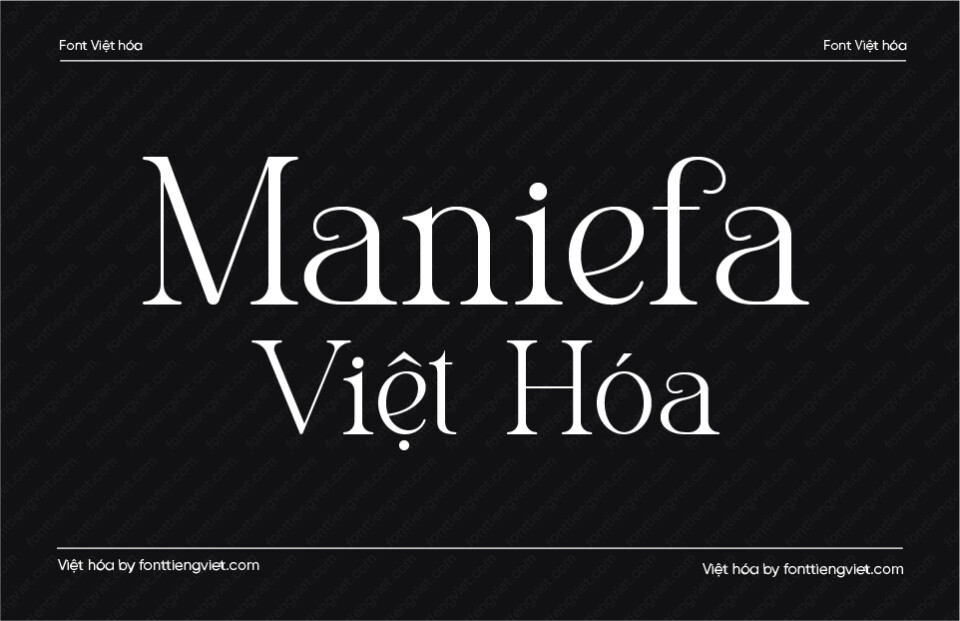
Font Việt hóa 1FTV VIP Maniefa – Bộ Font Sang Trọng Cho Thiết Kế Chuyên NghiệpTrong thế giới đồ họa hiện đại, việc lựa chọn một bộ Font Miễn Phí chất lượng luôn là ưu tiên hàng đầu của các nhà thiết kế. Font Việt hóa 1FTV VIP Maniefa nổi lên như một hiện tượng nhờ sự kết hợp hoàn hảo giữa nét cổ điển và hơi thở đương đại. Đây là bộ font chữ được tinh chỉnh kỹ lưỡng, giúp người dùng tại Việt Nam dễ dàng truyền tải thông điệp mà không lo lỗi hiển thị tiếng Việt. Với những đường nét thanh mảnh nhưng chắc chắn, bộ font này thực sự là giải pháp tối ưu cho những ai đang tìm kiếm sự khác biệt và đẳng cấp trong từng con chữ.Khám phá vẻ đẹp độc đáo của Font Việt hóa 1FTV VIP Maniefa sở hữu cấu trúc hình học cân đối, tạo cảm giác dễ nhìn và chuyên nghiệp. Điểm nhấn của bộ font này nằm ở các nét serif tinh tế, giúp tăng cường khả năng đọc trên cả nền tảng in ấn lẫn kỹ thuật số. Khi sử dụng bộ chữ này, các thiết kế của bạn sẽ tự động toát lên vẻ sang trọng, lịch lãm, phù hợp cho nhiều mục đích khác nhau từ làm thương hiệu đến trang trí nội dung học tập.Ứng dụng đa dạng trong thiết kế đồ họaVới sự linh hoạt cao, Font Việt hóa 1FTV VIP Maniefa thường được ưu tiên sử dụng trong các mẫu thiết kế thiệp mời, bìa sách hoặc tiêu đề tạp chí. Trong môi trường giáo dục, giáo viên và học sinh có thể dùng font chữ này để làm slide thuyết trình thêm phần cuốn hút và chuyên nghiệp hơn. Những đường nét mềm mại nhưng dứt khoát của Maniefa giúp làm nổi bật các ý chính, giúp người xem dễ dàng ghi nhớ thông tin một cách tự nhiên nhất.Sự tối ưu cho tiếng Việt chuẩn xácMột trong những lý do khiến Font Việt hóa 1FTV VIP Maniefa được yêu thích chính là việc tích hợp đầy đủ các dấu thanh tiếng Việt. Các ký tự như “ă”, “â”, “ơ” hay các dấu hỏi, ngã được thiết kế đồng bộ với thân chữ, tránh tình trạng bị lệch dấu hay thay đổi định dạng đột ngột. Điều này cực kỳ quan trọng đối với các bạn học sinh khi làm bài tập lớn hoặc các nhà thiết kế cần sự chỉn chu tuyệt đối trong văn bản tiếng Việt.Tại sao nên lựa chọn Font Việt hóa 1FTV VIP Maniefa?Việc sở hữu Font Việt hóa 1FTV VIP Maniefa không chỉ giúp bạn tiết kiệm thời gian chỉnh sửa mà còn nâng tầm giá trị thẩm mỹ cho tác phẩm. Bộ font này hỗ trợ nhiều định dạng khác nhau, tương thích tốt với các phần mềm phổ biến như Adobe Photoshop, Illustrator hay Microsoft Word. Sự tỉ màng trong khâu việt hóa giúp font chữ này giữ nguyên được linh hồn của bản gốc nhưng vẫn rất gần gũi với người dùng Việt Nam.Cách kết hợp font chữ hiệu quảĐể phát huy tối đa sức mạnh của Font Việt hóa 1FTV VIP Maniefa, bạn nên kết hợp nó với các font không chân (sans-serif) đơn giản cho phần nội dung dài. Sự tương phản giữa nét sang trọng của Maniefa ở tiêu đề và sự gọn gàng của font nội dung sẽ tạo nên một bố cục hài hòa, dễ chịu cho mắt người đọc. Đây là quy tắc vàng giúp bản thiết kế của bạn trở nên tinh tế và đẳng cấp hơn hẳn các mẫu thông thường.Kết luận về bộ Font Việt hóa 1FTV VIP ManiefaTóm lại, Font Việt hóa 1FTV VIP Maniefa là một công cụ không thể thiếu trong kho tài nguyên của bất kỳ ai yêu thích cái đẹp và sự chuẩn xác. Dù bạn là một học sinh đang làm báo cáo hay một designer chuyên nghiệp đang xây dựng bộ nhận diện thương hiệu, bộ font này đều đáp ứng xuất sắc mọi yêu cầu khắt khe nhất. Đừng bỏ lỡ cơ hội sở hữu Font Miễn Phí, Font Việt Hóa, Font Việt hóa 1FTV VIP Maniefa để biến những ý tưởng sáng tạo của mình thành hiện thực một cách ấn tượng và đầy cảm hứng ngay hôm nay.
Font Việt hóa 1FTV VIP Maniefa